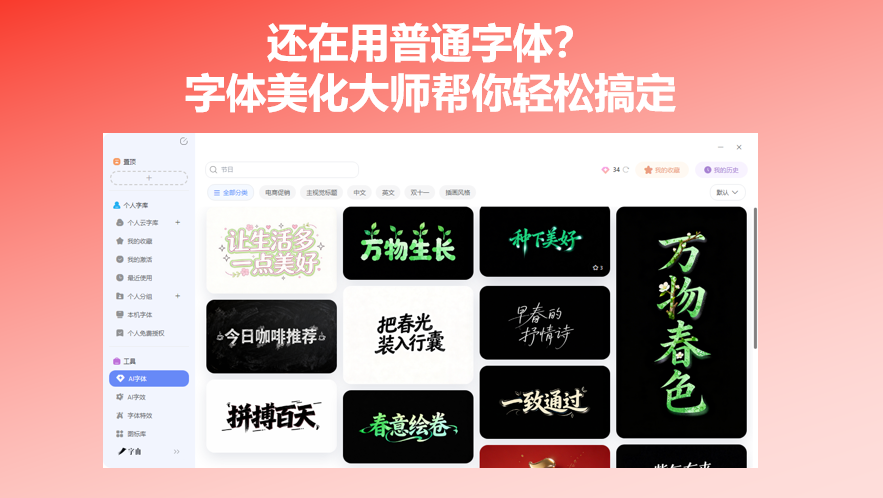
还在用普通字体?字体美化大师帮你轻松搞定
发朋友圈想用花体字,做海报想用艺术字,但电脑里翻来翻去就是宋体、黑体等系统自带的字体。想下载新字体又怕付费相关问题,或者下载了一堆以后想要后面再用的时候找起来很费劲。但是现在有了很多工具可以帮你解决这个问题,我管它们叫字体美化大师——输入文字,选个样式,就能生成好看的艺术字或花体字。今天我就整理了5个不同方向的美化工具,从设计师专业级的字体管理平台,到免费手写体下载站,再到一键复制粘贴的花体字生成器,覆盖了不同场景的需求。需要的记得收藏!
字由是目前国内设计师用得最多的字体管理与 AI 字体平台之一,它其实就相当于一个字体美化大师——从选字体、预览效果,到一键应用到设计软件,全流程覆盖。为什么这么说?因为它有着一个相当大的字体库美化:字由收录了上万款字体,其中免费商用字体超过 3500 款。打开字由客户端,在筛选栏里按“书法体”“手写体”“创意字体”等分类浏览,或者直接搜索“手写”“毛笔”“卡通”等关键词,就能找到适合你项目风格的字体。每款字体都有在线预览功能,输入自己的文案实时看效果,不用下载就能知道适不适合。
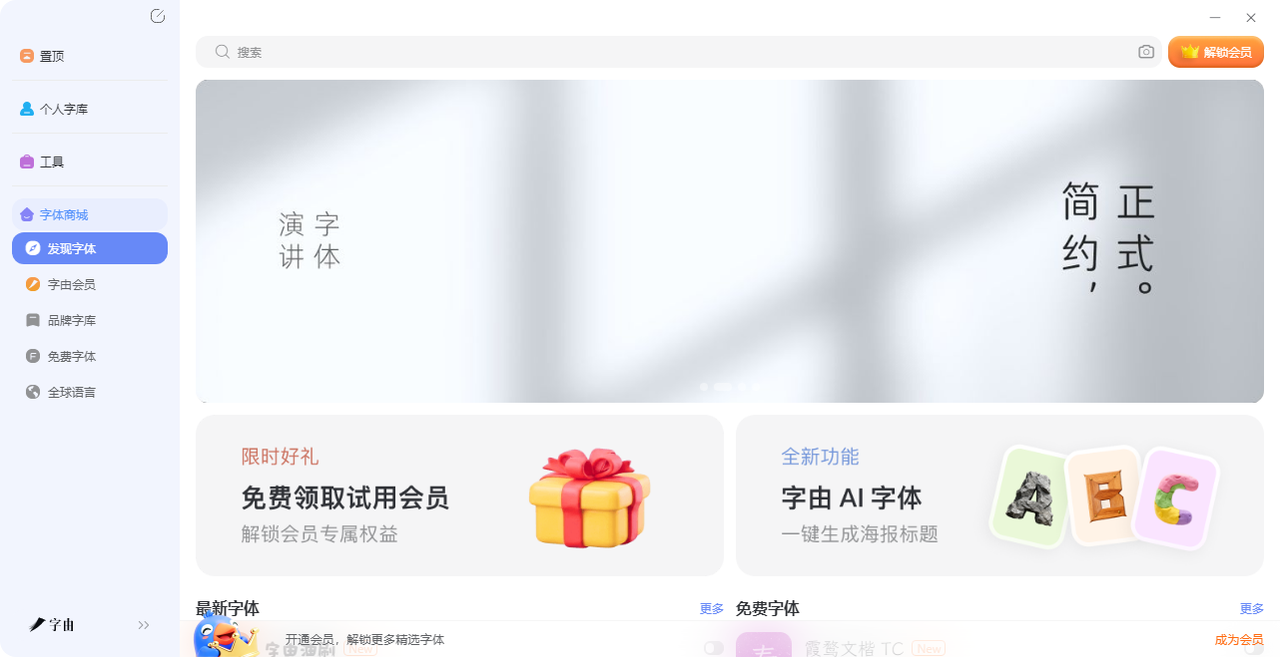
还有一个使用思路,那就是字由的AI字体:如果你连字体都懒得选,字由的 AI 字体功能可以直接生成艺术字图片。打开“AI 工具”,里面有多种特效模板,输入你的文案,选一个模板,10 秒左右就能生成一张带特效的艺术字图片,下载 PNG 就能直接用在海报或封面上。对于经常做设计的人来说,字由确实是一个名副其实的字体美化大师。
2、Online Fonts:Beautification
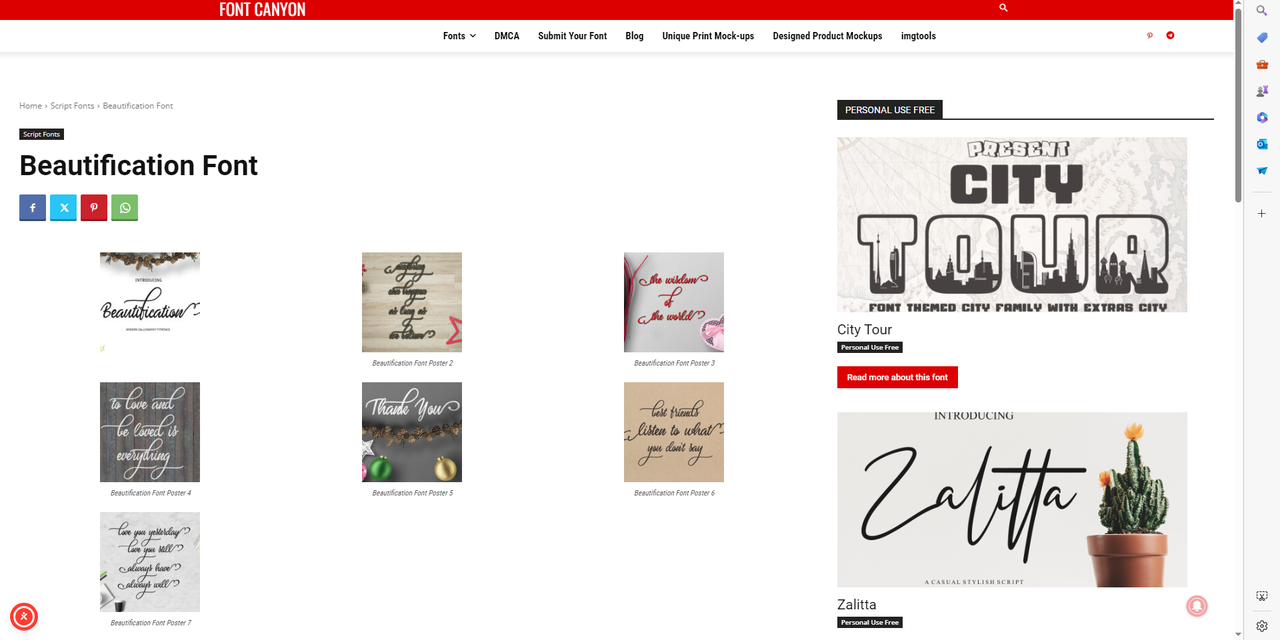
3、Font Canyon:Beautification Font
第三个网站是 Font Canyon,也是一个字体下载平台。同样提供了一款名为 Beautification Font 的手写体,但从截图看风格和 Online Fonts 那款不同——这款更偏向于现代手写体,笔画更粗犷,带有一种随性的涂鸦感。Font Canyon 将这款字体归类为“Script Fonts”(手写体/脚本字体)。页面上展示了多款类似风格的手写体,比如 City Tour、Zalitta 等。授权标注为“PERSONAL USE FREE”,即个人使用免费。如果你需要做婚礼请柬、个人博客标题、手账素材等,这类手写体能快速提升文字的美感。
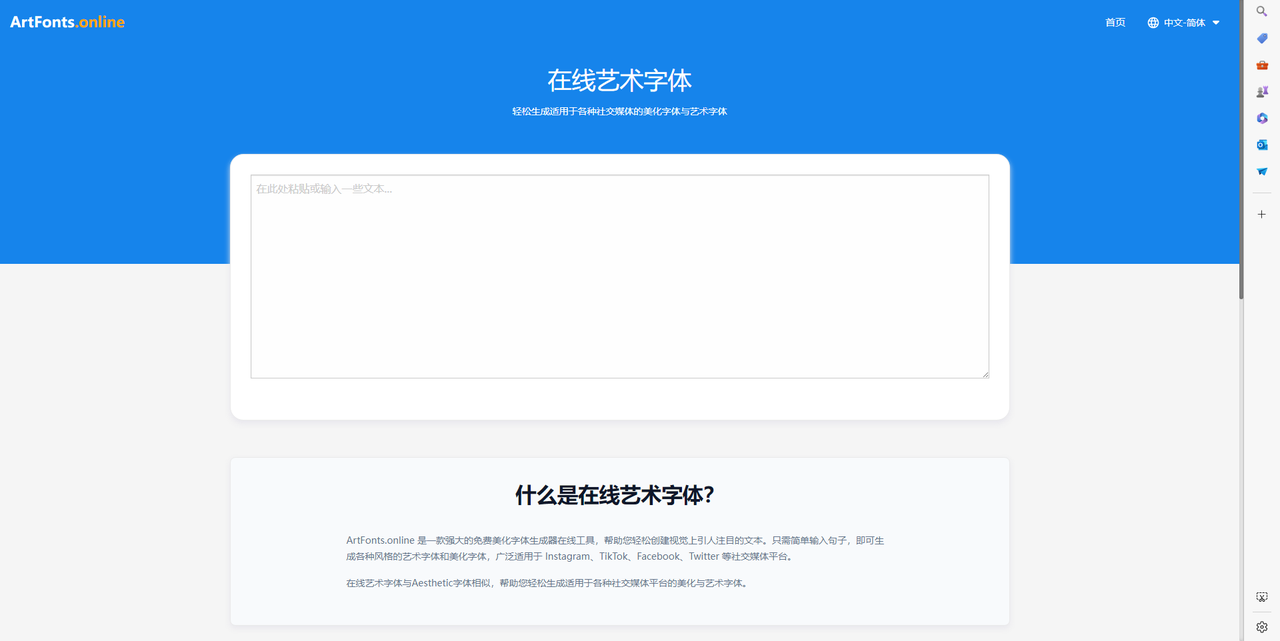
4、ARTFONTS
第四个网站是ArtFonts.online,一个专门做在线艺术字体生成的中文工具。界面简洁,核心功能就是输入文字,生成各种美化字体。它自称“强大的免费美化字体生成器”,主要面向 Instagram、TikTok、Facebook、Twitter 等社交媒体平台。它的工作原理和常见的 Unicode 花体字生成器类似——输入文字后,系统会转换成多种风格的花体、粗体、草书、哥特体等,然后一键复制粘贴到社交平台使用。
这个网站的优势是全中文界面,操作门槛低,不需要注册登录。如果你只是想发一条花体字朋友圈,或者给抖音简介加点个性,它是一个很方便的选择。它的字体样式数量不算特别多,但覆盖了常用的花体、气泡体、哥特体等,日常够用。
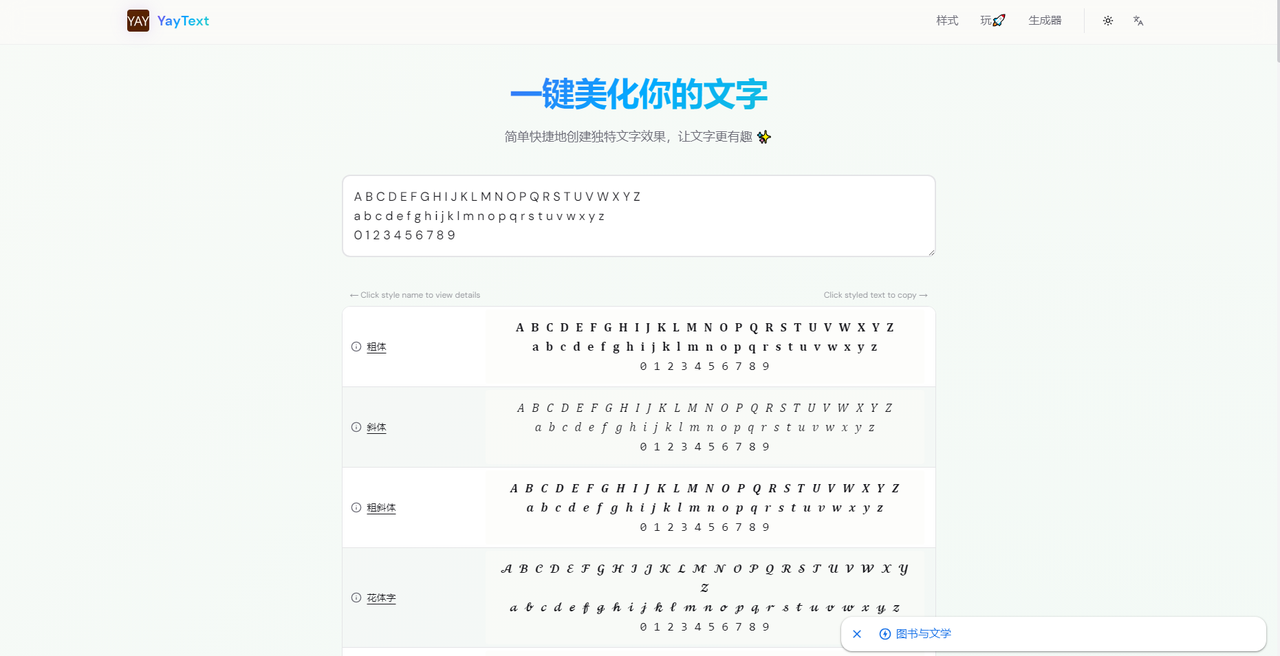
5、yaytext
第五个工具是 yaytext(yaytext.app/zh),一个支持多语言的在线花体字生成器。yaytext 的特色是界面干净、响应快,支持中文、英文、日文、韩文等多种语言的字体美化。输入文字后,它会生成几十种不同风格的 Unicode 花体字,包括粗体、斜体、花体、哥特体、双线体、小型大写等。每种样式旁边都有一个“复制”按钮,点一下就能粘贴到任何地方。yaytext 还提供了“随机生成”功能,如果你不确定想要什么风格,点一下随机按钮,它会帮你随机展示一种样式,给你一些灵感。这个工具完全免费,不需要注册,也没有广告干扰,使用体验比较清爽。
对于经常需要在社交媒体上发花体字的用户来说,yaytext 是一个值得收藏的工具。它的中文字体转换支持也不错,相比一些只支持英文的生成器更实用。
以上介绍的这5 个工具,对应不同的字体美化需求。字由是最全面的,从字体库选型、一键激活到 AI 艺术字生成,适合设计师和专业用户;Online Fonts 和 Font Canyon 提供具体的手写字体下载,适合需要安装字体文件做本地设计的用户;yaytext 是在线花体字生成器,输入文字复制粘贴就能用,适合普通用户在社交媒体上使用。不过最后我还是最推荐字由,毕竟有两条思路供你选择,如果你有感兴趣的话就快打开官网尝试一下吧!